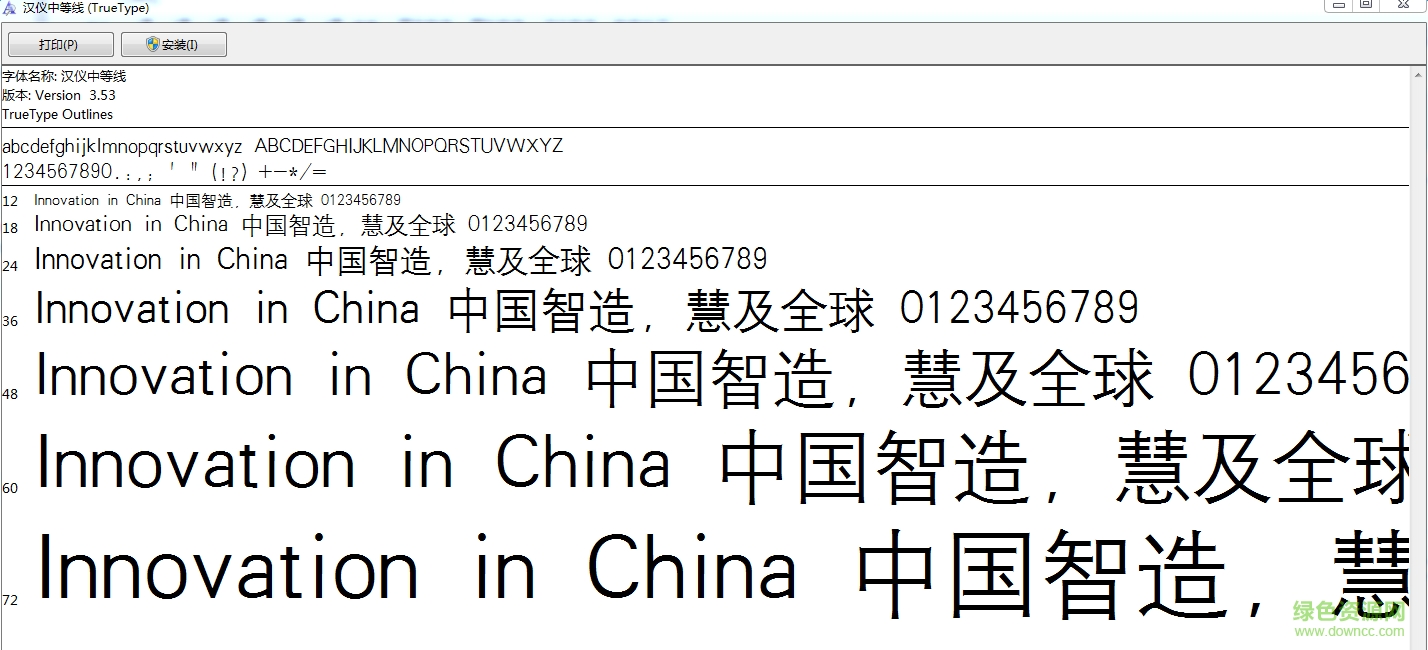
hyg2gj(漢儀中等線簡)字體是一款沒有字腳的漢儀等線體,該字體骨骼端正,筆畫線條十分清晰,字形樸素大方,各種領域都可使用,喜歡的朋友快來綠色資源網下載吧!
hyg2gj字體介紹
hyg2gj字體是一款漢儀類線狀簡體字體,中等線形的字體給人非常簡約清新的感覺,字形秀美,婷婷玉立,可廣泛應用于正文書寫、平面廣告設計、印刷包裝、電視媒體等領域。